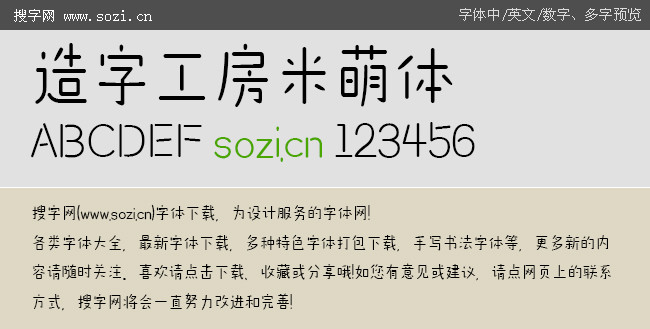
造字工房米萌體
搜字網(wǎng)給大家提供一款造字工房米萌體中文字體下載,該字體以稚童學(xué)字之筆意為基本設(shè)計理念,結(jié)構(gòu)松散有度,處理靈活多變、錯落有致,散亂錯落處盡顯質(zhì)樸幼拙、天真爛漫之意趣,能夠適用于產(chǎn)品包裝、廣告宣傳、海報設(shè)計、網(wǎng)頁廣告設(shè)計等應(yīng)用。(本字體為個人非商用版,如需要商用請聯(lián)系官方購買版權(quán))